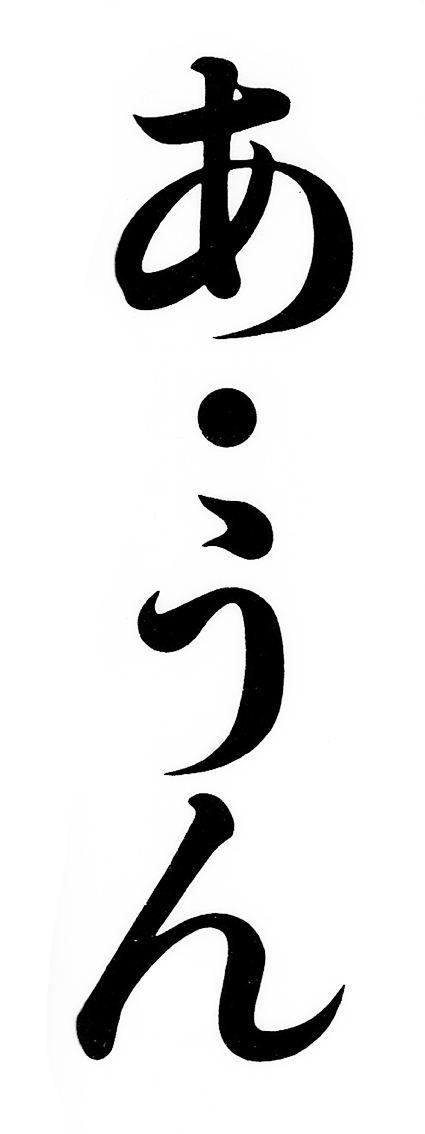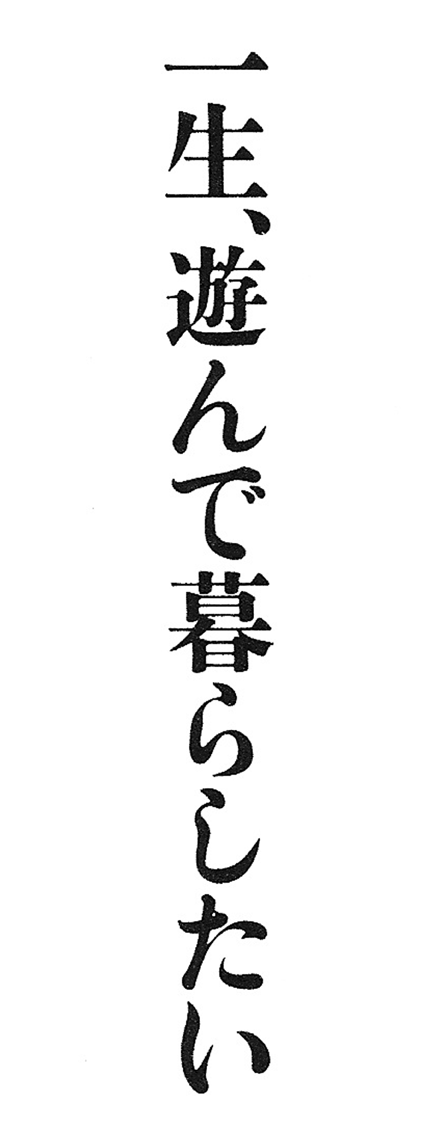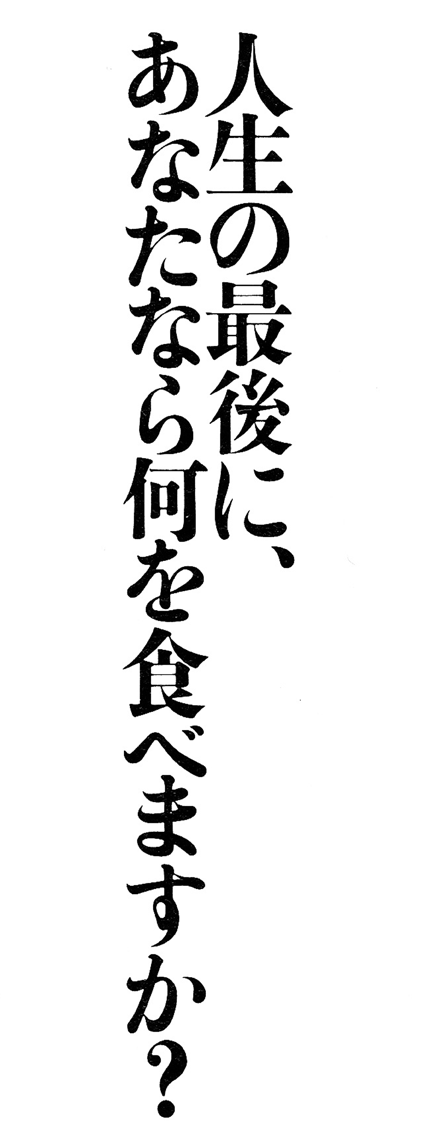
かな民友明朝
昔から知ってはいるけれど、自分では一度も口にしたことのない言葉のひとつに「蕎麦をたぐる」という表現がある。
きどった感じがして気恥ずかしいし、何より似合わない。漠然と男性語のような気がしていたのは、江戸っ子や噺家のイメージがあるからだろうか。
でも、実を言うと、「蕎麦をたぐる女」にちょっと憧れる。
蕎麦をたぐる女は、きっとお酒も強いにちがいない。夕方からひとりで蕎麦屋にでかけてもさまになり、長尻はしないが、隣り合わせに野暮な客がいればピシャリと言い放つ。「蕎麦は喉で味わうものよ」なんてね。
見出し用のかな書体〈かな民友明朝〉でかかれた言葉も、「読む」というよりは「たぐる」という気分がしっくりくる。重みのある、ダイナミックな強い線。たくみな筆の運びには、交互に息を吸ったり、吐いたりするようなリズムがあって、文字を目で追うのではなく、言葉を手繰り寄せている感覚にとらわれる。
〈かな民友明朝〉は写研の写植書体の名前だれど、資料によると、そのルーツは、東京築地活版製造所で明治二十年頃につくられた初号活字にあるという。
「初号」というのは活字のいちばん大きなサイズのこと。活字制作の技術が中国から日本に伝わって以来、書道ではありえなかった「(活字のコマの)正方形の四角い枠のなかに文字をおさめる」ことと仮名の美しさを初めて両立させたのが〈築地体初号活字〉だった。
この活字が民友社に提供され、後に写研やモリサワが写植書体の原字として採用することになる。さらに現在では〈游築初号かな〉というデジタルフォントも同じ字形をベースにしており、時代が変わっても脈々と受け継がれている貴重な書体のひとつだ。
私自身はこの書体を古典として眺めたことはないけれど、つい引き比べてしまうのが、もうひとつの代表的な初号活字、〈秀英初号明朝〉である。
私にとって〈秀英初号明朝〉が水のなかの世界みたいに静かで、超然とした印象であるのに対し、〈かな民友明朝〉でかかれた言葉は音のある世界、地上の世界だ。同じストイックでも、どこか人間くさいというか、道楽の気配が漂うというか、私財をなげうって楽しみごとをきわめたような気迫なのである。
はたして、この書体のもとになった初号活字の制作者が何者なのか、それは残念ながらわかっていない。
でもこの字をみていると、ひょっとしたら、あのヴァン・ゴッホのように、世間の評価や名声とは縁遠い、放蕩の限りをつくした人生だったのではないか。そんな荒唐無稽な想像までしてしまう。
「カッコつける」ということは「無理をする」ということである。
中場利一のエッセイに、そんな言葉が書かれていた。その点では江戸と大阪も似たようなものだなと思う。「見栄をはる」ということ。
その精神は、案外、あらゆるデザインの原点になっているのかもしれない。
日本人の意地と誇りが、庶民の食卓を粋な舞台へと昇華させてしまったように。